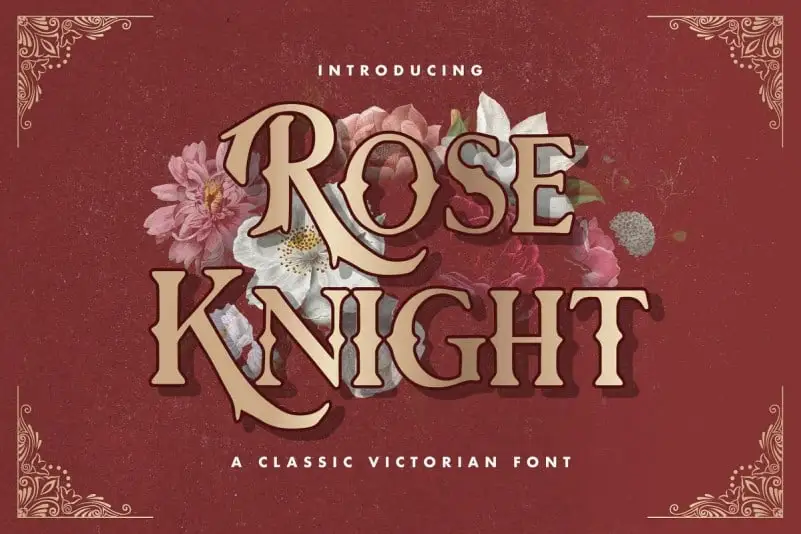
Rose Knight Display Font
A Rose Knight Display Font é uma elegante e única fonte vintage inspirada nos movimentos artísticos e arquitetônicos decorativos. Desenhada pelo talentoso designer StringLabs, esta font oferece um toque único que remete à era dos detalhes delicados. Ideal para projetos de design, headlines, materiais de propaganda, logotipos, selos, camisetas e muito mais, a Rose Knight promove criatividade e beleza em seu uso. Seja você um estilista, designer gráfico ou freelancer, esta fonte é perfeita para levar seus trabalhos digitais ao próximo nível de sofisticação e originalidade.